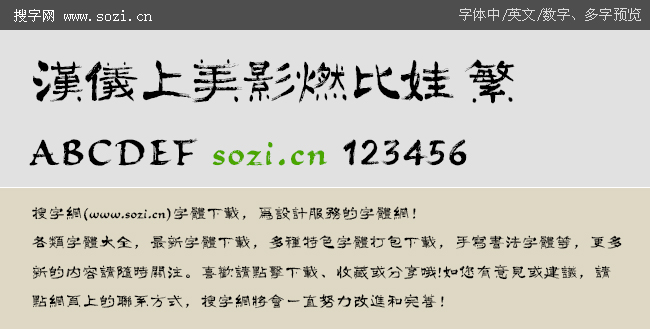
漢儀上美影燃比娃 繁
搜字網(wǎng)給大家提供一款漢儀上美影燃比娃 繁中文字體下載,漢儀上美影燃比娃字體是一款手寫風(fēng)格的毛筆字體,字體筆畫隨性大方,結(jié)構(gòu)肆意灑脫,整體效果非常不錯。適用于畫冊設(shè)計、海報設(shè)計、包裝設(shè)計等場合使用。(本字體為個人非商用版,如需要商用請聯(lián)系漢儀公司購買版權(quán))